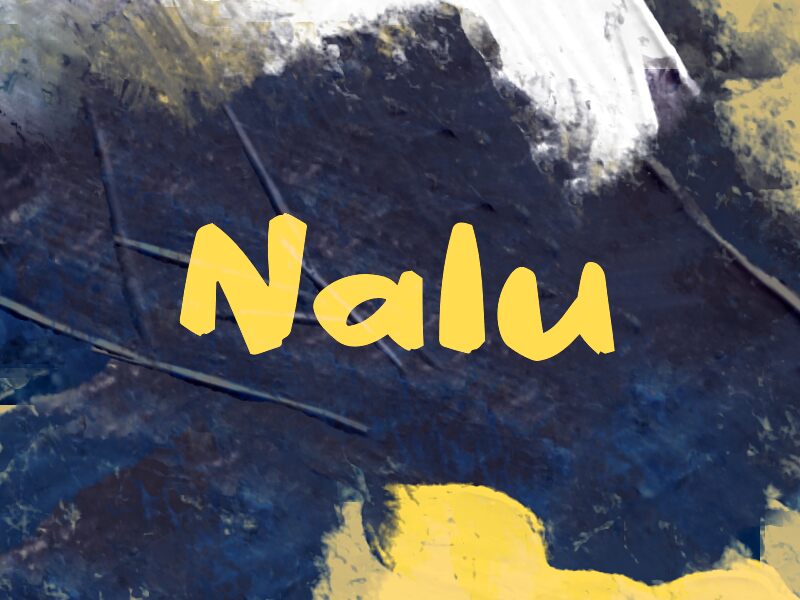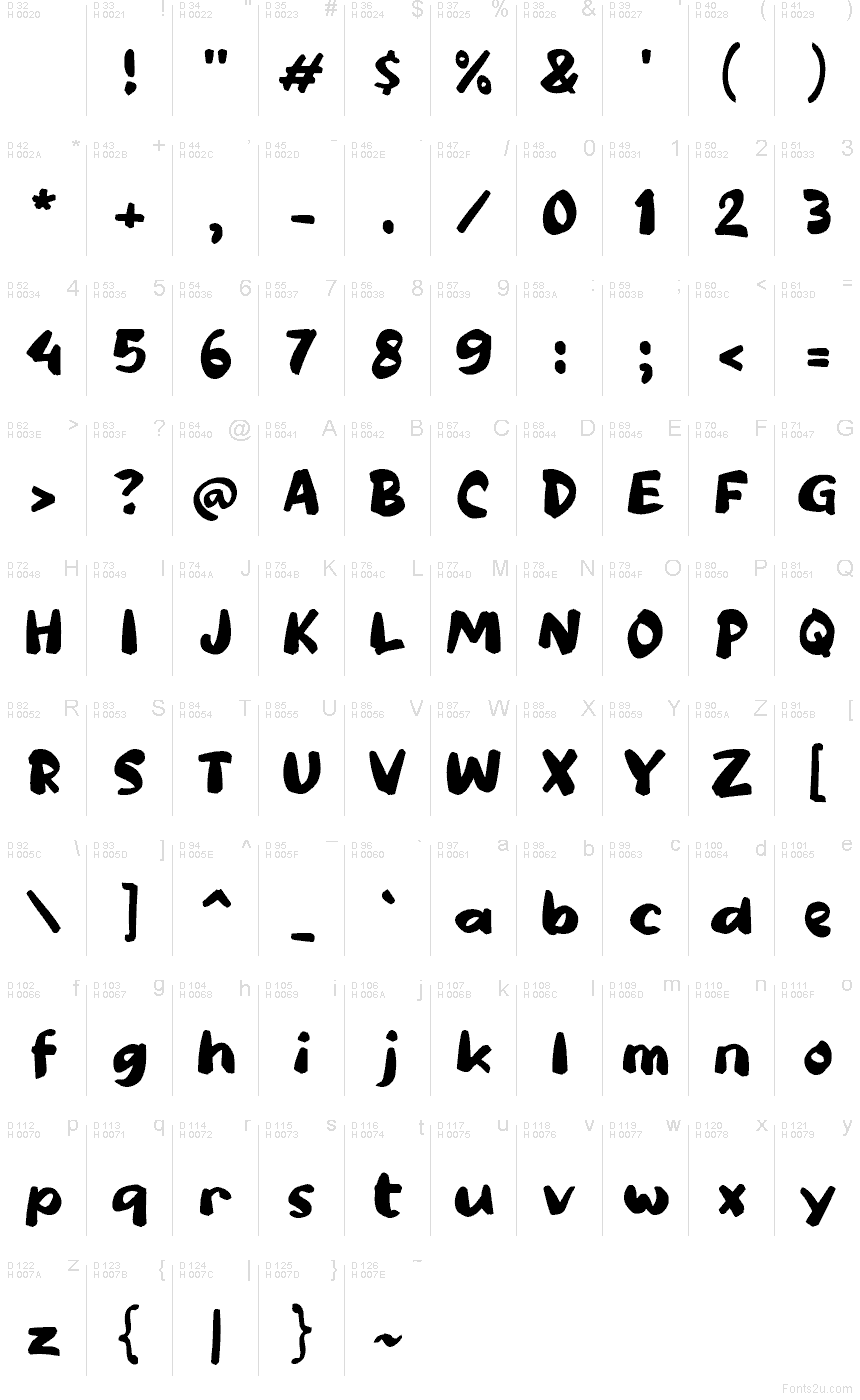
Nalu
Nalu di Wep è un font brush gratuito che evoca l'atmosfera rilassata dei cartelli da spiaggia. Le lettere sembrano tracciate con un pennello carico di colore, caratterizzate da tratti spessi, curve morbide e bordi irregolari che danno al tutto un ritmo dinamico e naturale, tutt'altro che rigido.
È perfetto per i titoli di poster, il branding di caffè, copertine di album, packaging informali e grafiche per i social dove serve un tocco fatto a mano. Come font gratuito, Nalu è ideale soprattutto per brevi titoli, bozzetti di loghi e scritte di copertina: le sue forme ampie e corpose e il movimento rapido del pennello conferiscono anche alle parole brevi una presenza calda e accogliente.